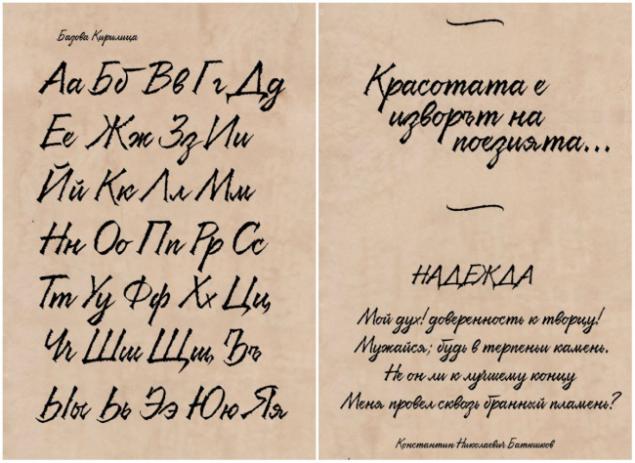
16 лучших бесплатных кириллических шрифтов 2016 года — Оди
Акцидентный шрифт, основанный на каллиграфии Дарьи Квон. Он был начат на онлайн-курсе «Свой шрифт» в TypeTypeSchool в августе 2016 года. Шрифт содержит базовый набор кириллических знаков, а также расширенную кассу знаков для латиницы.
Акцидентный гротеск с узкими пропорциями и низким контрастом, созданный на основе допетровской кириллицы и стилизованный под модерн. 2 начертания: обычное и наклонное. Мультиязычный: латиница, кириллица, расширенная латиница, расширенная кириллица.
Подойдёт для заголовков и небольших объёмов текста, логотипов и иллюстраций, плакатов и упаковки.
Гарнитура из дополняющих друг друга нео-гротесков и рукописных шрифтов. Бесплатно одно начертание. Дизайнер Ани Петрова, Фонтфабрик.
Акцидентный шрифт, стилизованный под антикву нового стиля.
Немного зауженный гротеск с достаточно качественной кириллицей. Все 8 начертаний гарнитуры бесплатны для личного и коммерческого применения.
Гуманистический гротеск с кириллицей. В гарнитуре 8 обычных начертаний и 8 курсивных. Бесплатно раздают 2 начертания, Медиум и Медиум Италик. Остальные продаются по 25$ за штуку или за 320$ за все. Дизайнер Глен Жан из Уфы.
Слово авторам: «Нежный и добрый цветочный шрифт, который производит впечатление своей естественной красотой. Шрифт Магнолия — это определенно девушка, можно даже сказать шрифтесса, которая расцвела и готова подарить свою красоту окружающему миру».
Автор шрифта Таня Черкиз, арт-директор Иван Гладких, инженер шрифта Денис Сериков.
Бесплатный декоративный шрифт.
Частично бесплатный узкий гротеск с кириллицей. Бесплатно можно скачать 4 узких начертания: Light, Light Italic, Extra Bold и Extra Bold Italic. Полная гарнитура Muller из 44 шрифтов обойдется в 279$. Можно покупать отдельные начертания по 47$.
Бесплатный гротеск с кириллицей. Дизайнер шрифта Сергей Рядовой, в качестве арт-директора выступил известный шрифтовой дизайнер Иван Гладких (TypeType). В шрифте качественная кириллица, а также поддержка многих других языков.
Антиква с кириллицей в 6 начертаниях (одно бесплатно, остальные по 1400₽). Автор Миша Панфилов.
Новый бесплатный шрифт с кириллицей. Шрифт создан на основе популярных в 60-е буквенных форм (см. надписи на ст. метро «Таганская» и «Коломенская» московского метрополитена), но в своём развитии отошёл достаточно далеко от прототипа. Oks может применяться в кеглях от 36 и выше (можно и ниже, но в таком случае потребуется принудительная разрядка).
Серия из трех рукописных шрифтов.
Рукописный шрифт с «партизанским» характером. Автор Карлос Зубия из Мексики.
30 лучших бесплатных рукописных шрифтов для дизайнеров в 2019 году • Оки Доки
List предлагает на выбор 30 рукописных шрифтов, которые все бесплатны для коммерческого использования, Хотя они не все новые, они являются испытанными и проверенными рукописными шрифтами, которые нам нравятся. Репозитории шрифтов классифицируют рукописные шрифты по-разному, поэтому некоторые из них могут быть помечены как «сценарий», «каллиграфический» или «декоративный», в зависимости от веб-сайта.
1. Подросток праздный
2. Античная книга
3. Как мило, как …
4. Дневник DP Dork
5. Ручная работа
6. Калам
Tragic Marker — это толстый рукописный шрифт, который, как следует из названия, напоминает аккуратный и жирный почерк толстого маркера.
Шрифт может использоваться в различных ситуациях, включая заголовки, электронные поздравительные открытки и дизайны, которые стремятся быть игривыми, но в то же время профессиональными.
8. Сценарий Шраг
Mervale — это скрипт-шрифт с характерным ретро-чувством, идеально подходящий для винтажного дизайна, смелых названий и цитат. Он сочетает в себе широкие и тонкие мазки и обладает отличным потоком, поэтому он не будет выглядеть неуместно даже на профессиональном веб-сайте или в журнале.
10. Блэк Джек
26. Пивные деньги
Пивные деньги действительно выделяются. Это рукописный шрифт с толстыми штрихами, который выглядит наброском и лучше всего подходит для гранж, неформального и постерного дизайна.
27. Диадема Хентимпса
Использование рукописного шрифта передаст аудитории, к которой вы стремитесь, элегантность и эксцентричность. Вы можете использовать рукописные шрифты в логотипах, кампаниях в социальных сетях, печатных материалах, прямой почтовой рассылке или вывесках, чтобы выделиться среди конкурентов.К счастью для вас, мы составили список лучших бесплатных рукописных шрифтов, которые вы можете использовать в своих проектах.